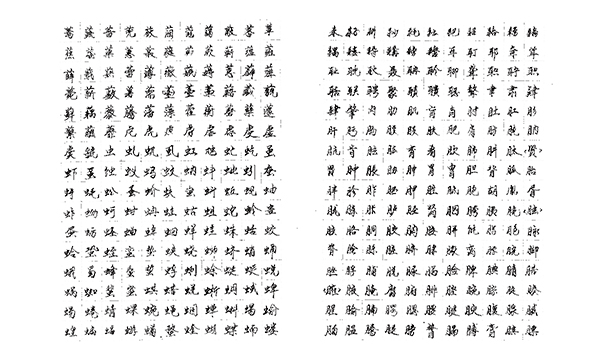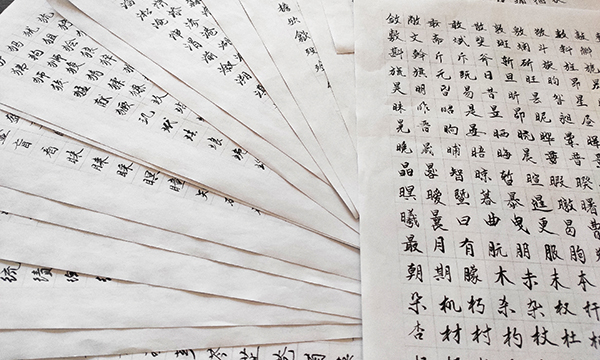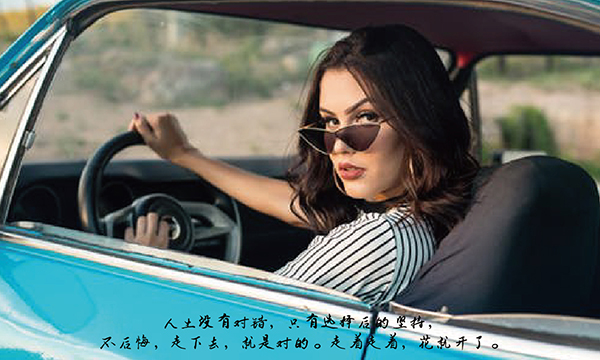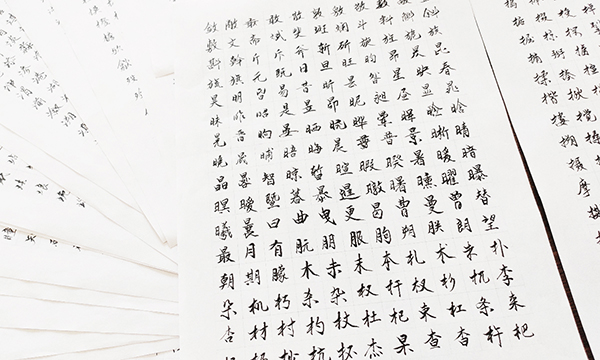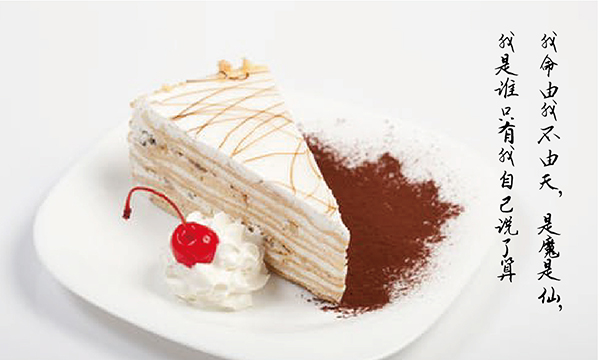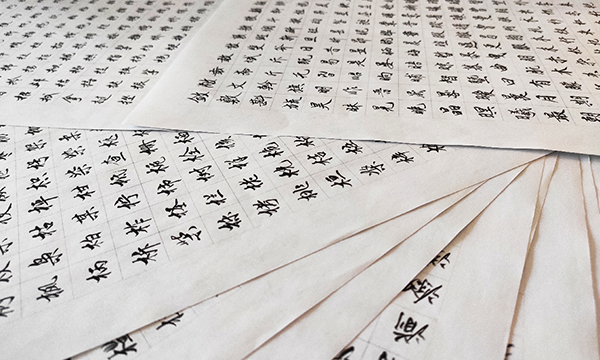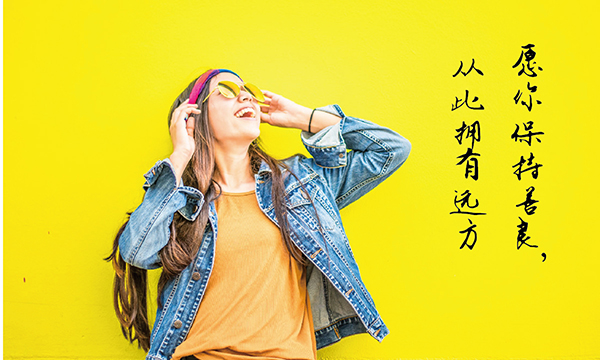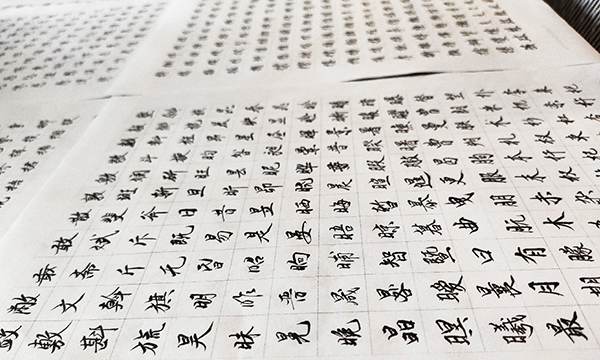
字体名称:新叶莹体
字库字数:简体+符号共计7123字
字体风格:柔和而坚毅
适用范围:品牌标志、广告、影视综艺、包装、漫画等
这副字体看上去温柔而遒劲,一笔一画之间抒写着一种外柔内刚的坚毅,横竖撇捺之间氤氲着一丝丝的灵动,像阳光下的玉石散发着淡淡的光彩,温和而不刺眼,寓意为“莹”这便是字体名字的由来了!
秀逸匀整的笔画横陈在每个文字间,透露着一种阴阳和谐之美,每一个文字的笔画都柔和平缓,避免了太过锋利,就像做人一样要磨平棱角处事,但也要保留自己的特色一样。
我们要告别千篇一律的生活,我们要穿着我们喜欢的衣服,吃着喜欢的美食,用着特别的字体发着微信、发着简讯给特别的人,传递特别的心意。